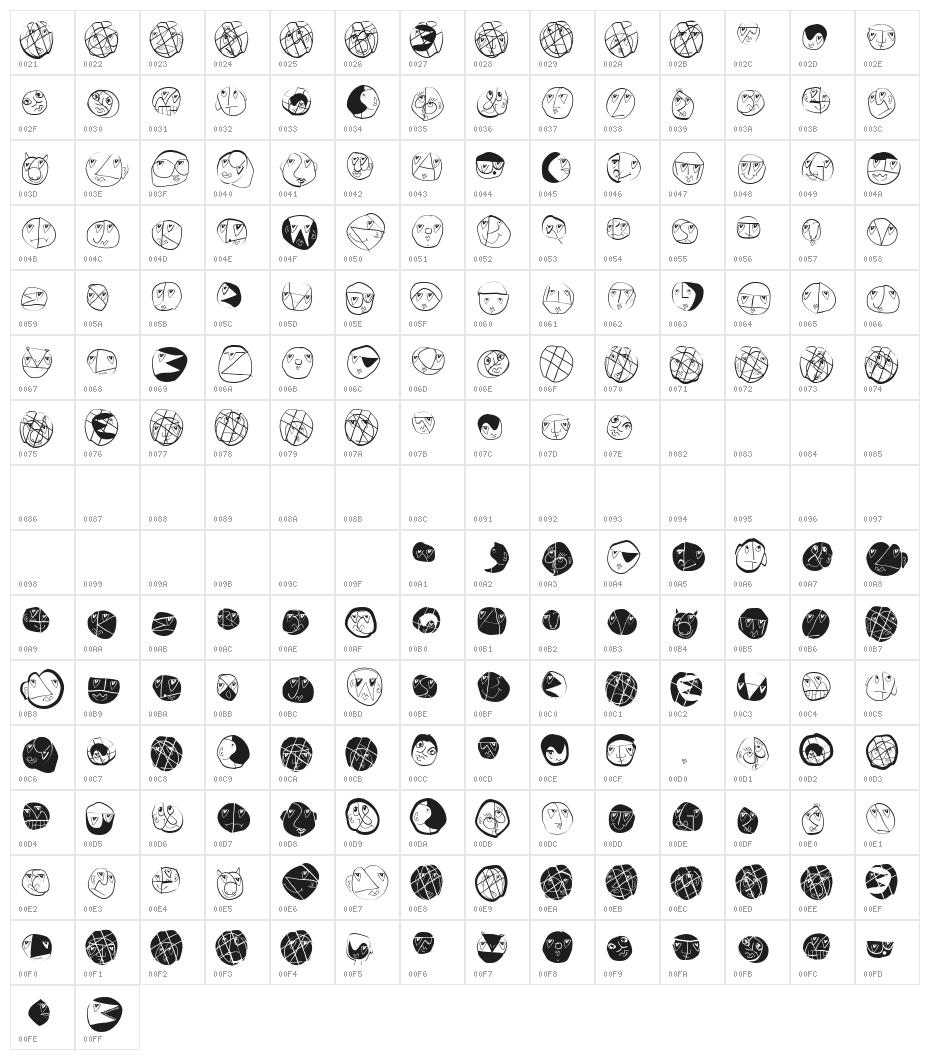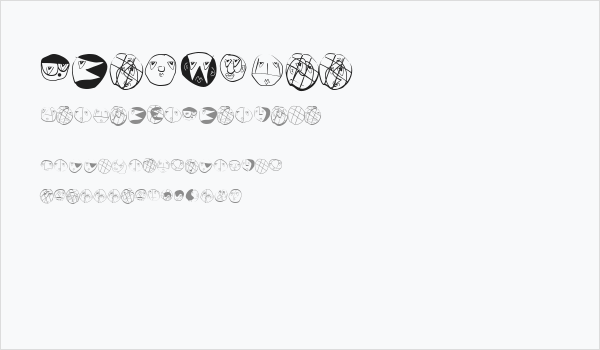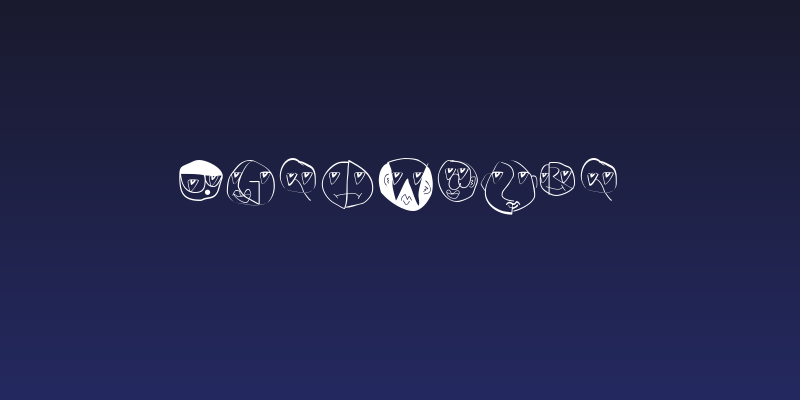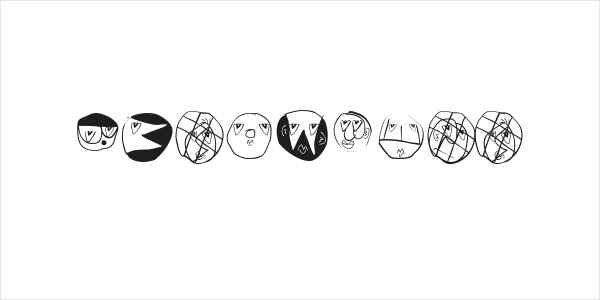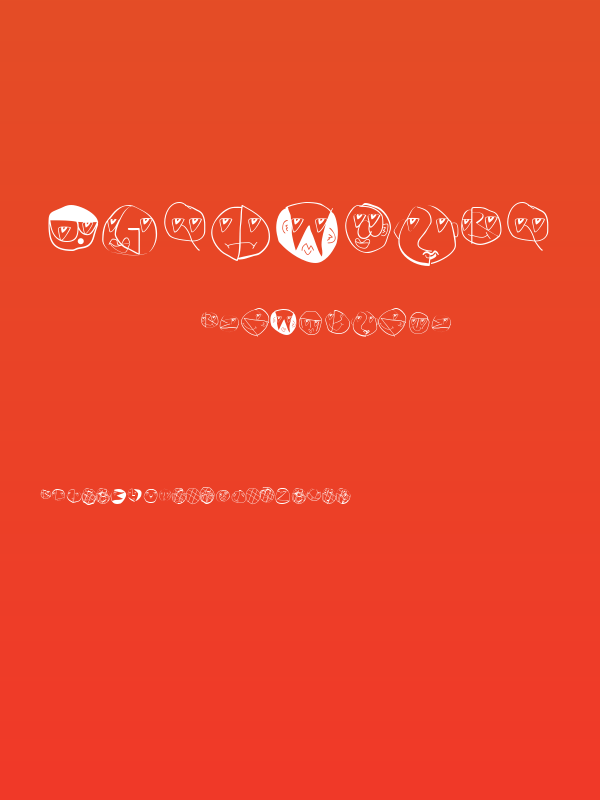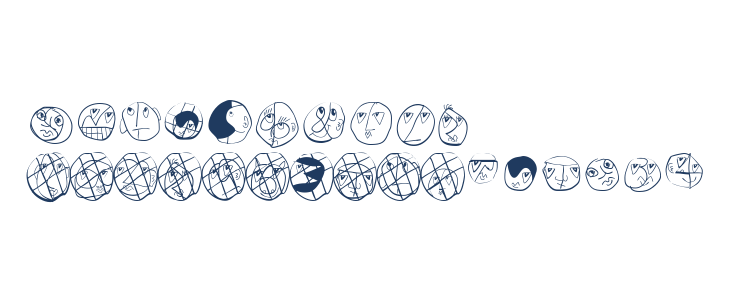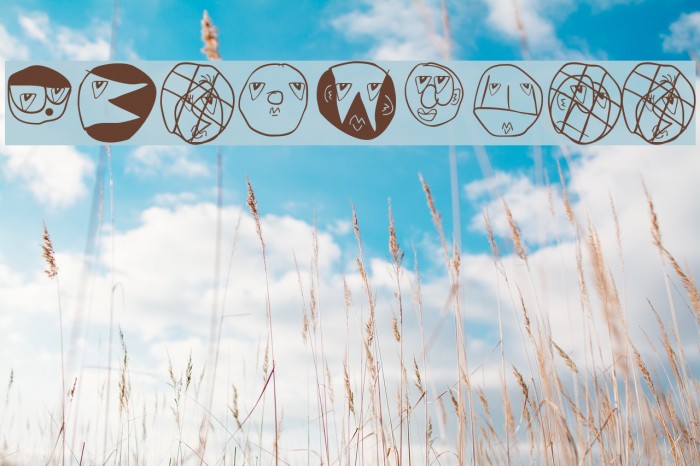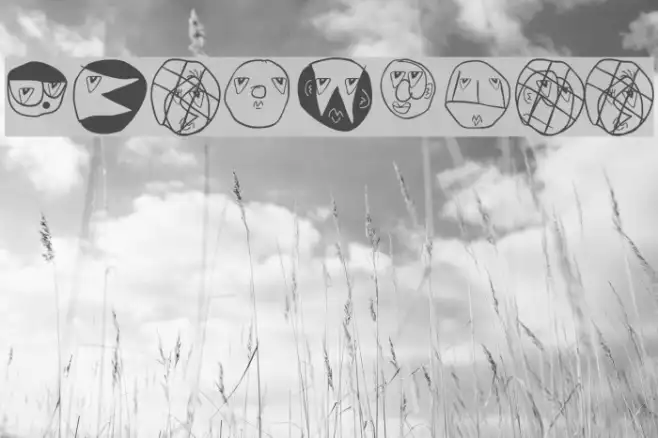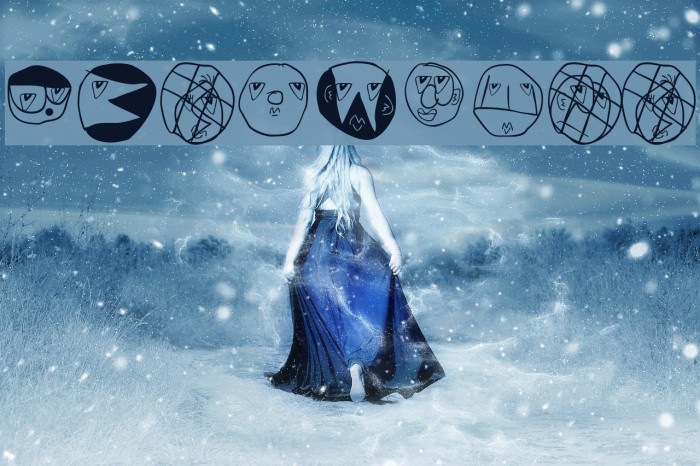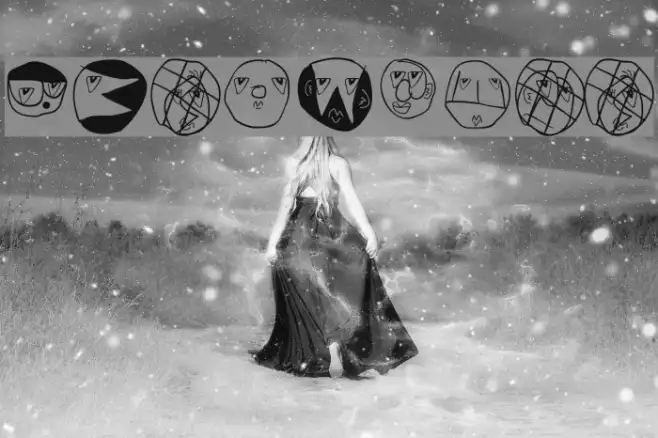
DiskOBats Font
| Stile generale | Artistic, Whimsical |
| Caso d'uso | Artistic designs, Posters, Album covers |
| Progetti proposti | Ideal for creative projects such as art posters, album covers, or any design work that benefits from a unique and playful visual element. |